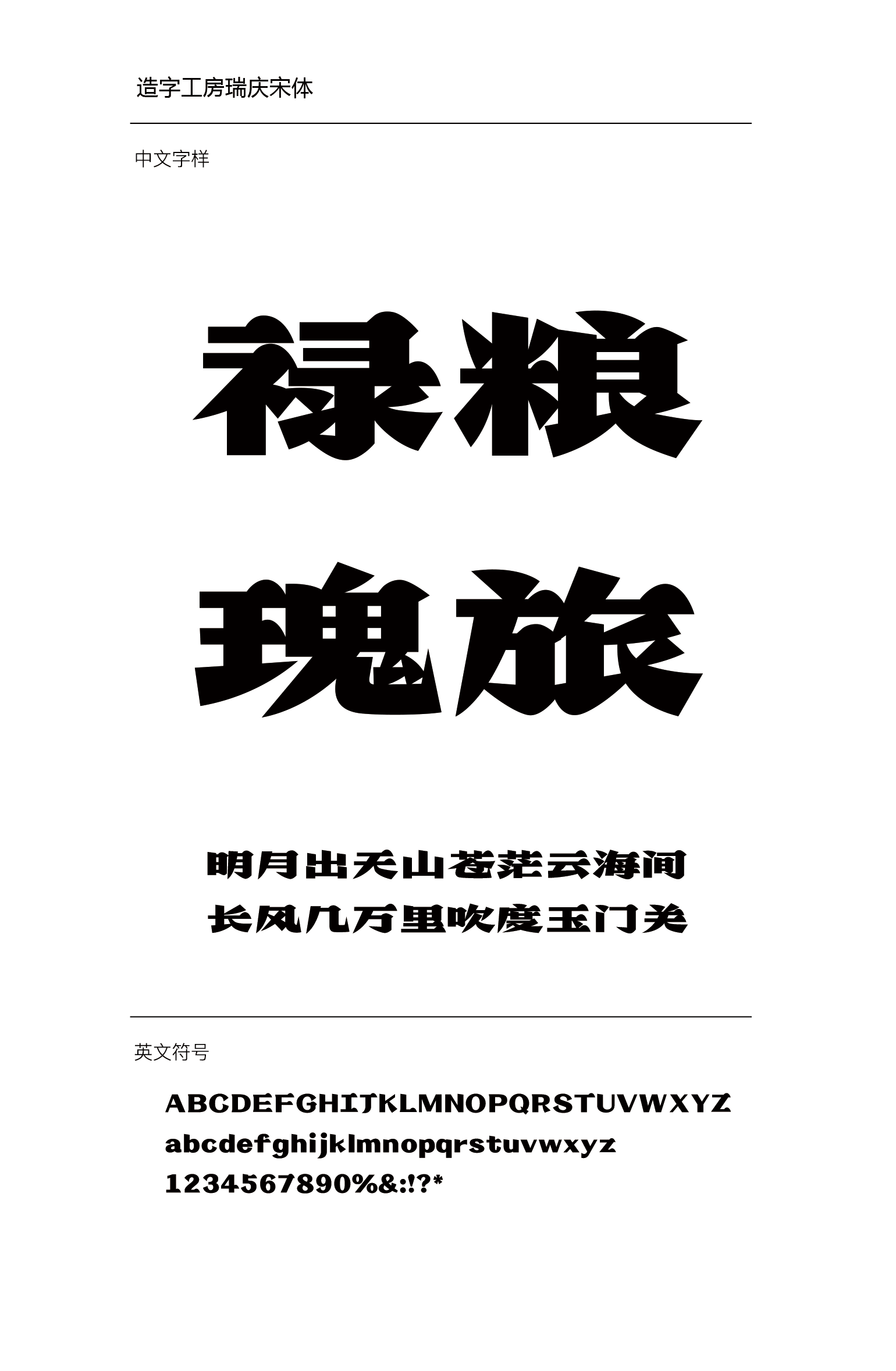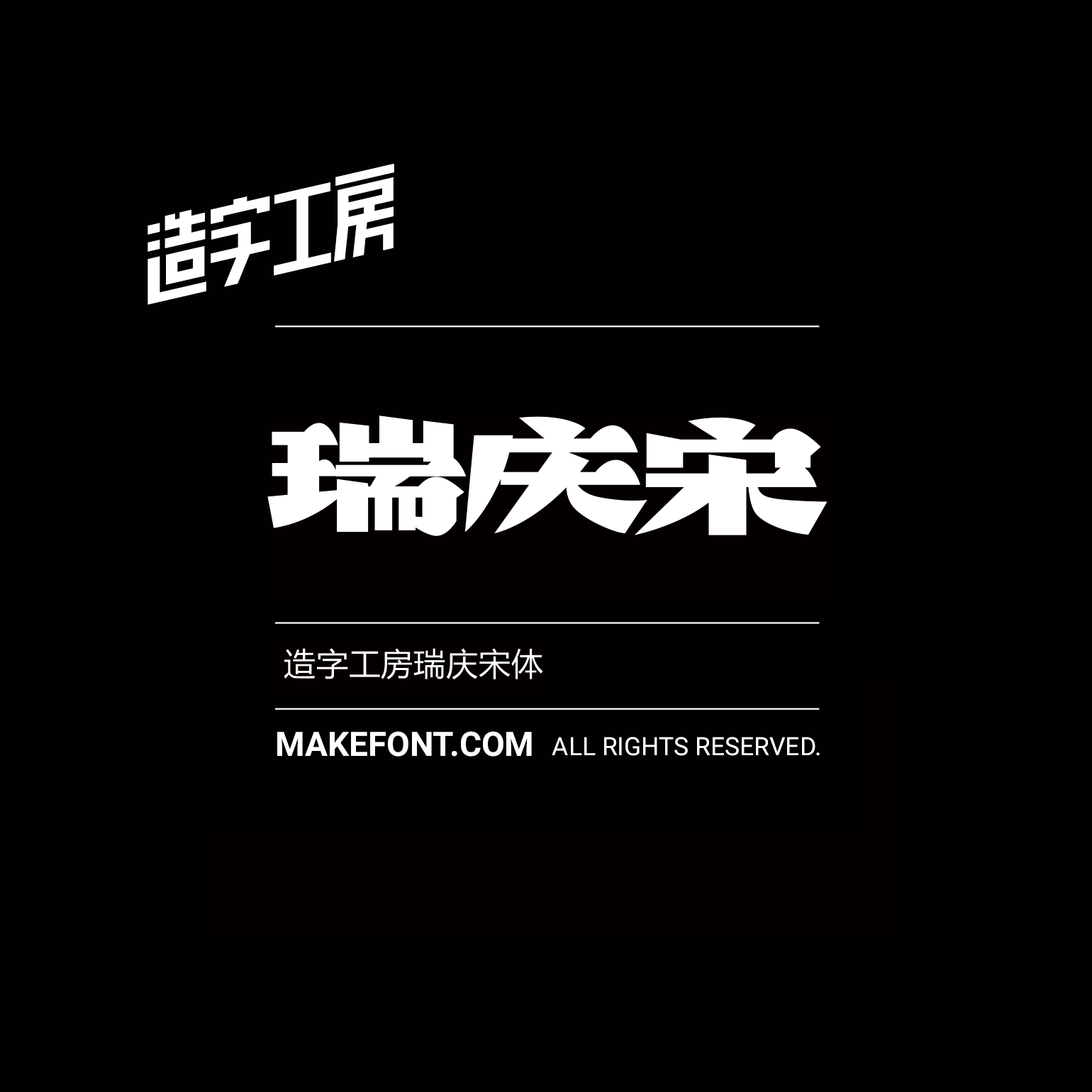
造字工房瑞庆宋体设计说明
造字工房瑞庆宋体,是一款巧妙融合宋体风骨与现代律动的创意字体。它保留了宋体标志性的笔画衬脚与优雅骨架,通过灵活的几何化处理,打破了传统的严谨框架。非常适合用于追求人文质感与当代设计感相结合的场合。本字体为简体字库,采用OpenType/CID格式,Adobe-GB1-5编码。基于中华人民共和国GB2312-80字符集标准,另按需添加101个汉字。共收容字数6864CJK汉字,ASCII常用字符100个。